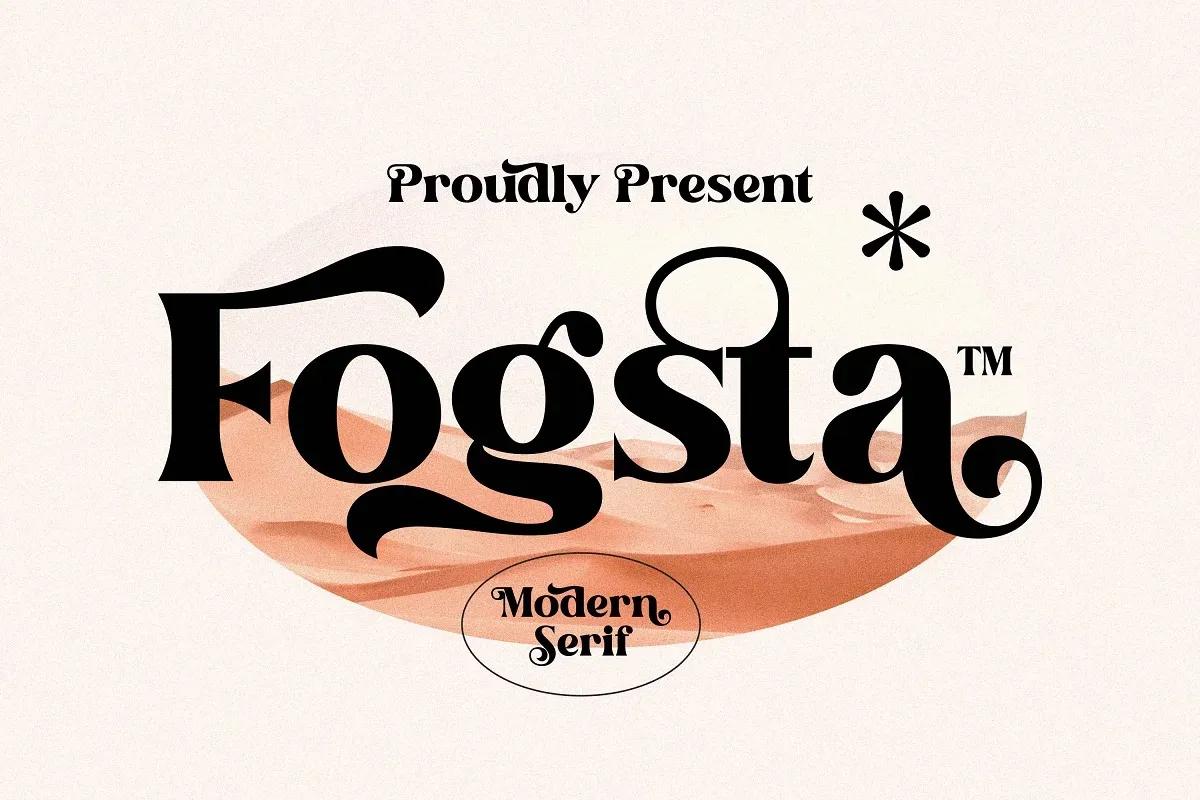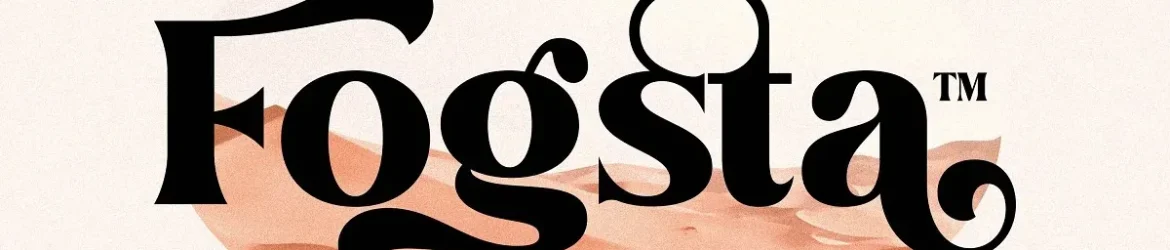
Fogsta Font – Download Grátis
A Fogsta é uma fonte serif bold vintage repleta de hedonismo e alegria de viver. Suas características fortes e sua facilidade de uso transmitem um senso de confiança que surge naturalmente. Ela se adequa perfeitamente para logotipos elegantes e luxuosos, títulos de livros ou filmes, marcas de moda, revistas, letras, citações e muito mais. Com a Fogsta, você ganha uma opção poderosa para estilizar seus projetos com estilo e sofisticação, tornando suas criações ainda mais impactantes.